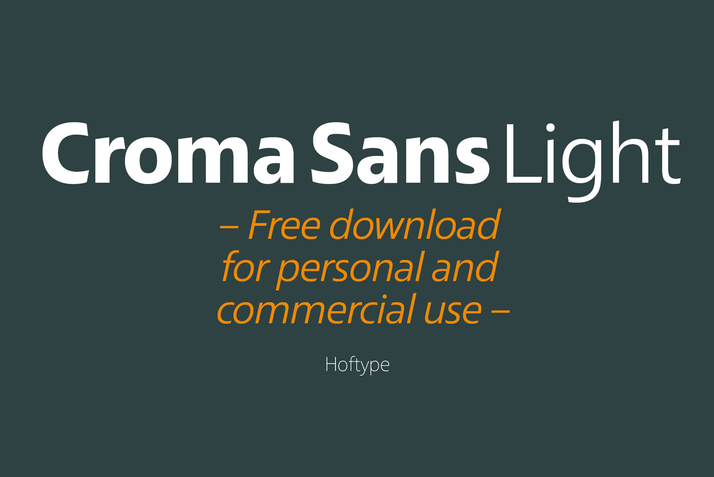
Croma Sans Font Family – Download Grátis
Introduzimos a você uma nova família de tipografia sans serif, Croma Sans Font Family. Desenvolvida pelo Hoftype, essa elegante e linear família de 16 estilos é perfeita para designers que buscam criatividade sem perder controle. Introduzida em 2016, Croma Sans oferece uma gráfica controlada e distintiva, perfeitamente adaptável a projetos de tipos ambiciosos. Perfeito tanto para designers digitais quanto para aqueles que trabalham com impressão digital, Croma Sans é um ótimo complemento para qualquer projeto. Suas linhas definidas tornam-o especialmente adequado para texturas visuais interessantes e para criar um contraste atraente em suas composições. Ideal tanto para aplicativos digitais quanto para a web, Croma Sans está sempre à altura da sua melhor obra. Sem dúvida, uma excelente opção para designers buscando dar vida aos seus projetos com elegância e modernidade.